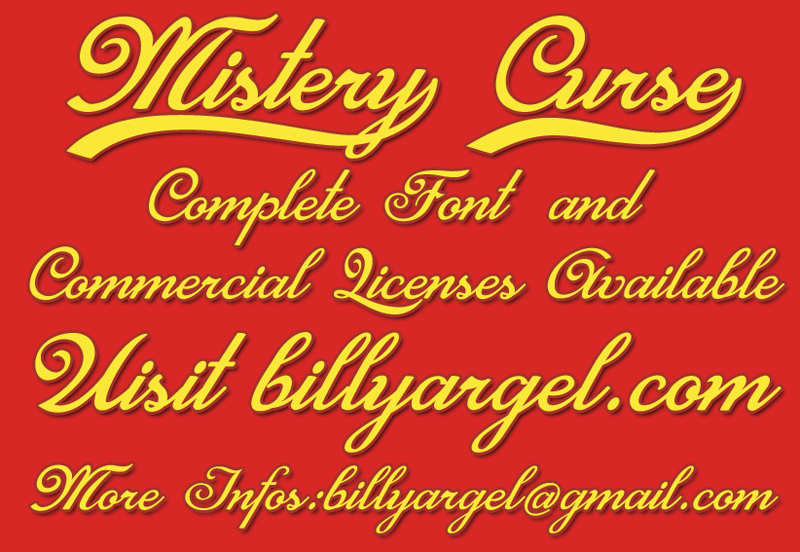
A Mistery Curse Font é uma obra-prima para amantes do chauvinismo tipográfico, criada pelo designer Billy Argel. Este fonte tem um caráter chamativo e peculiar, que oferece ao autor uma maneira de expressar a sua criatividade sem abrir mão da facilidade do uso personalizado. O valor mais apreciado por artistas e designers é a flexibilidade de uso pessoal e comercial. Esta fonte não só traz a habilidade de incorporar um design único em trabalhos pessoais, mas também oferece o reconhecimento adicional do mercado comercial. Além disso, Billy Argel disponibiliza mais informações e ajuda no seu website, bem como em suas redes sociais. Visite o site para obter detalhes sobre a fonte e saiba onde adquirir versões completas e licenças comerciais exclusivas. Ao usar Mistery Curse Font, você pode se tornar parte da incrível diversidade de criações do designer Billy Argel que traz um toque único à sua arte ou projeto. É uma maneira de manter a criatividade viva e relevante em nossos tempos digitais.